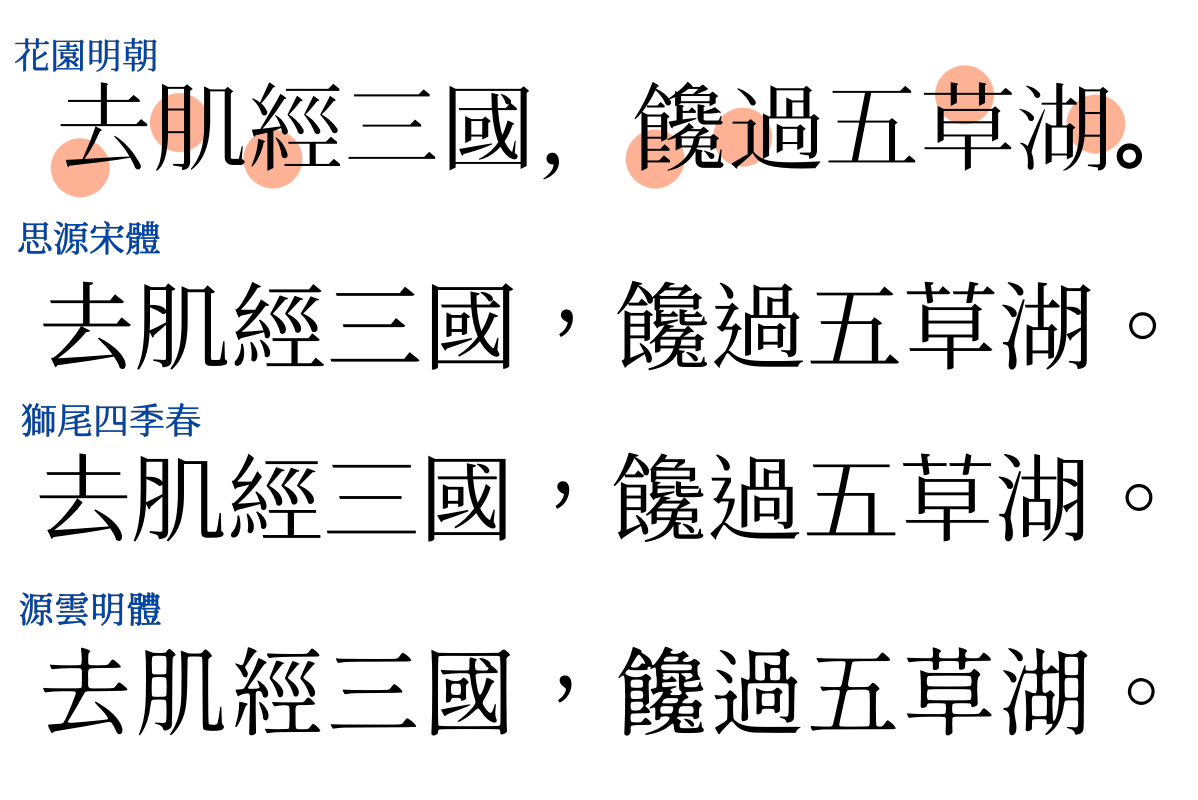
狮尾四季春
字体简介
“狮尾四季春”(LionTail Spring)是一款由台湾狮尾数位设计公司(LionTail Digital Design)推出的免费中文字体,最初发布于2020年3月。它属于衬线风格,基于传统宋体改良,笔画细腻优雅,带有古典书法的韵味,同时融入了现代设计的简洁感。这款字体提供单一字重(Bold),包含6763个汉字(符合GB2312标准),支持简体中文,以及部分英文和符号。
它的设计灵感据说来自四季常青的意象,字形挺拔,笔画起收有轻微粗细变化,适合用于书籍排版、海报标题或需要古典气息的文创设计。